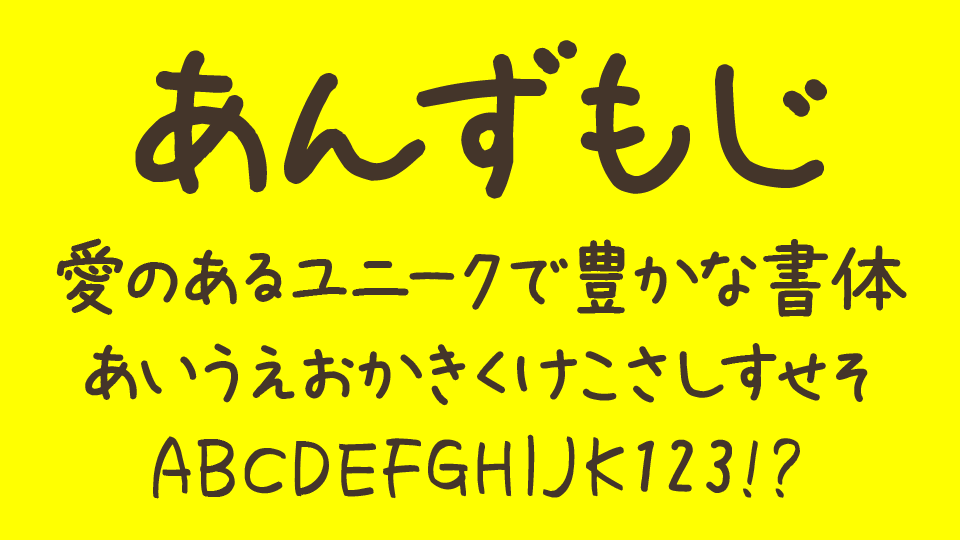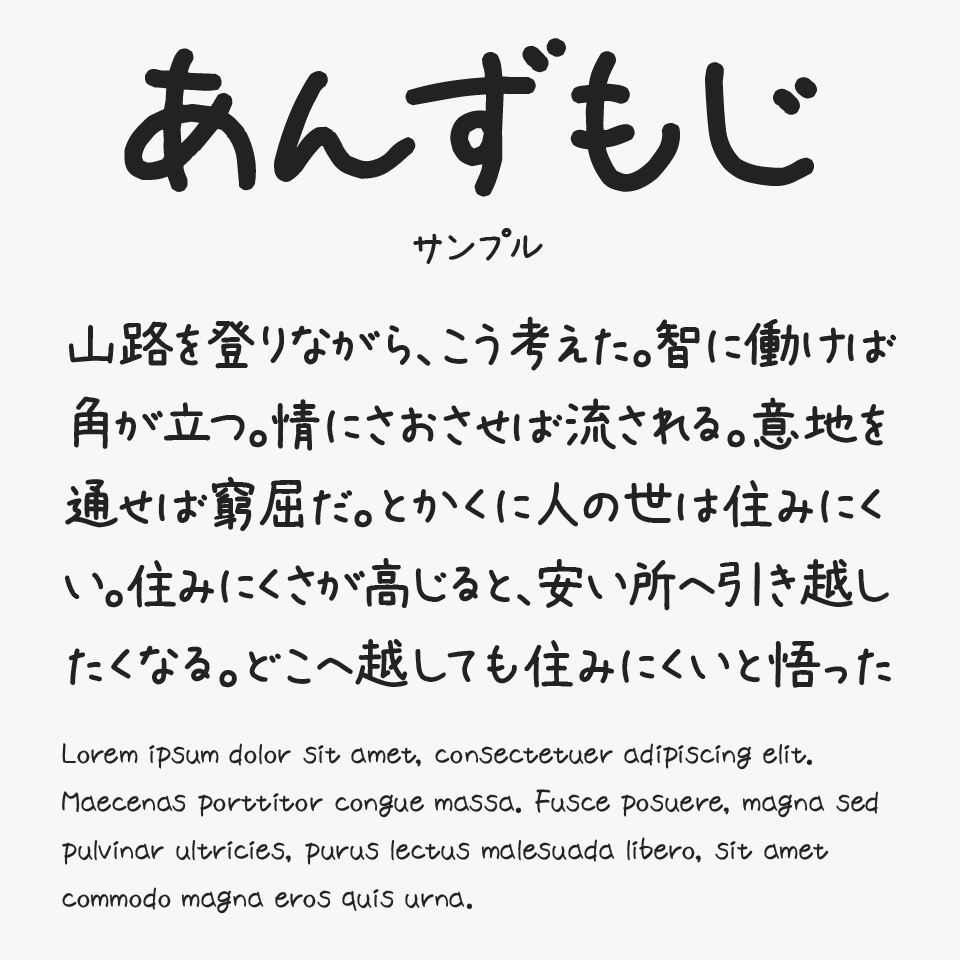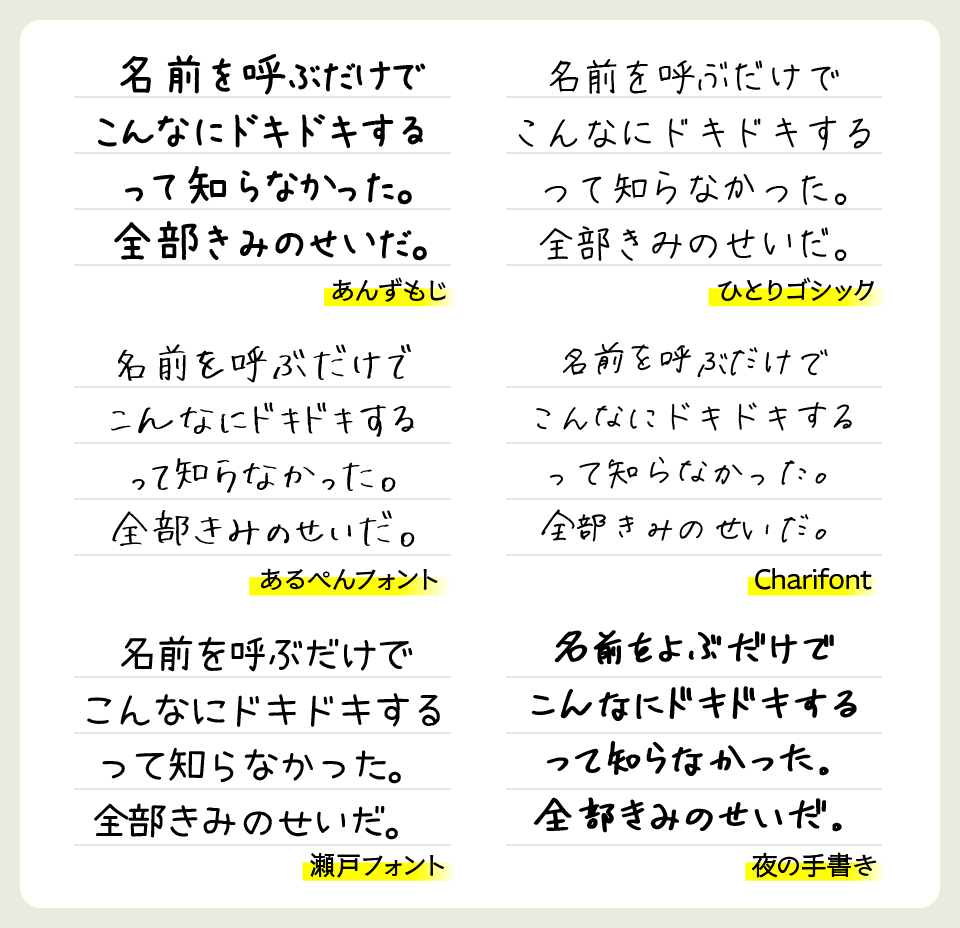
あんずもじフォントは、女性らしい小ぶりで可愛らしい雰囲気が魅力の手書きフォントです。
やさしく自然な文字の流れや、リアル感のある手書き質感によって、まるで実際にノートへ書かれたような親しみやすさがあります。
収録漢字数も多く、長文でも違和感なく使いやすいため、手書きフォントの中でも実用性が高いところも特徴です。かわいらしさはありつつも、クセが強すぎないため、ブログ・動画テロップ・サムネイル・雑貨デザインなど、さまざまなシーンで活躍してくれるフォントです。
自分自身も十数年前から使用させていただいているフォントの1つで、“定番の手書き書体”です。今では手書きフォントも数えきれないほど増えましたが、当時は「手書きフォントといえば、あんずもじ」と言われるほど人気があり、多くの人に親しまれてきた名作フォントのひとつです。
あんずもじ
あんずもじフォントを、ほかのやわらかい雰囲気を持つ手書きフォントと比較してみると、自然体で親しみやすい“リアルな手書き感”が特に魅力です。
比較フォントは、「ひとりゴシック」「あるぺんフォント」「Charifont」「瀬戸フォント」「夜の手書き」と使用していますが、どのフォントも独特なかわいい手書きがステキなので、ぜひあわせてチェックしてみてください。
あんずもじと「ひとりゴシック」「あるぺんフォント」「Charifont」「瀬戸フォント」「夜の手書き」を比較